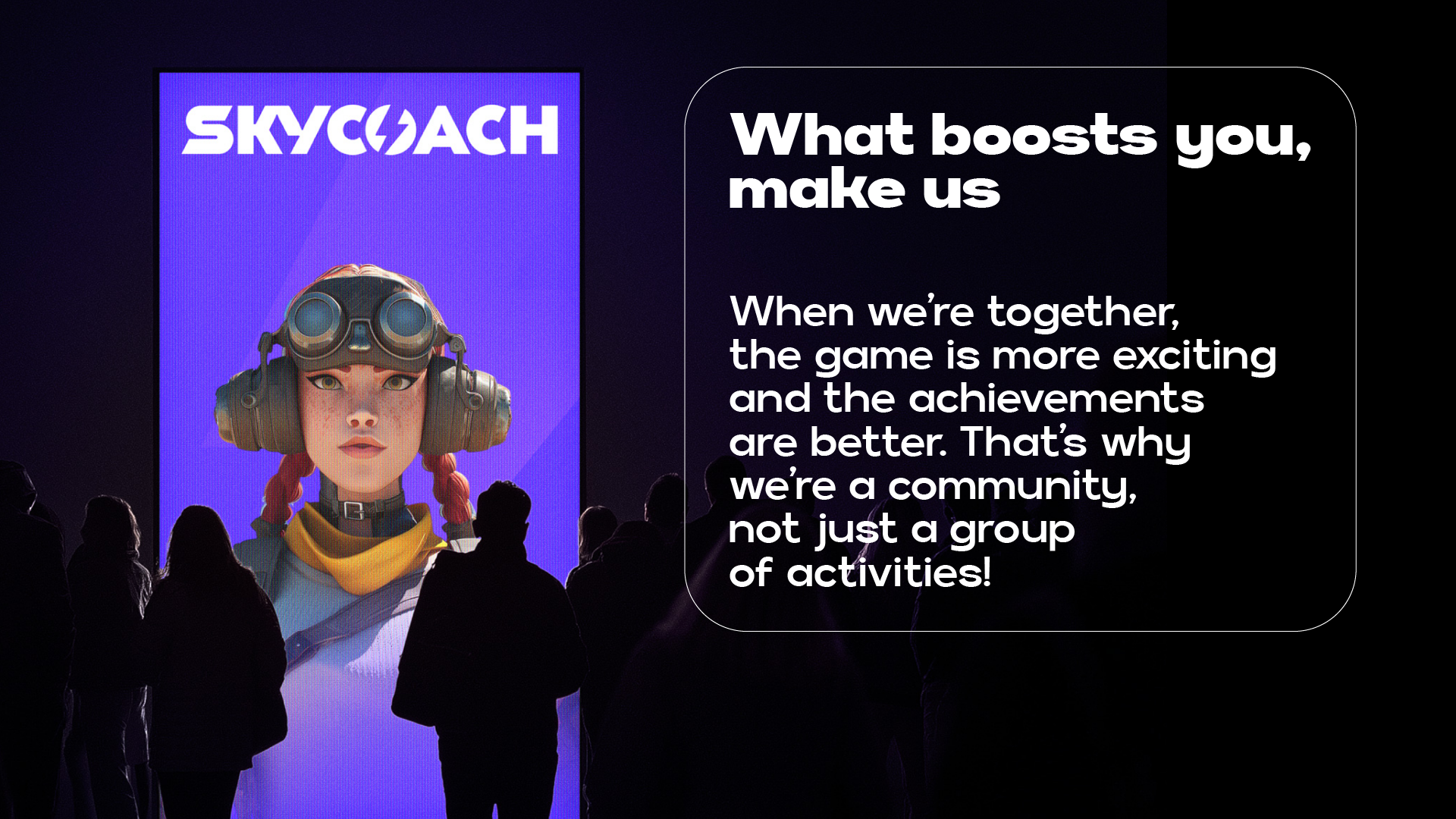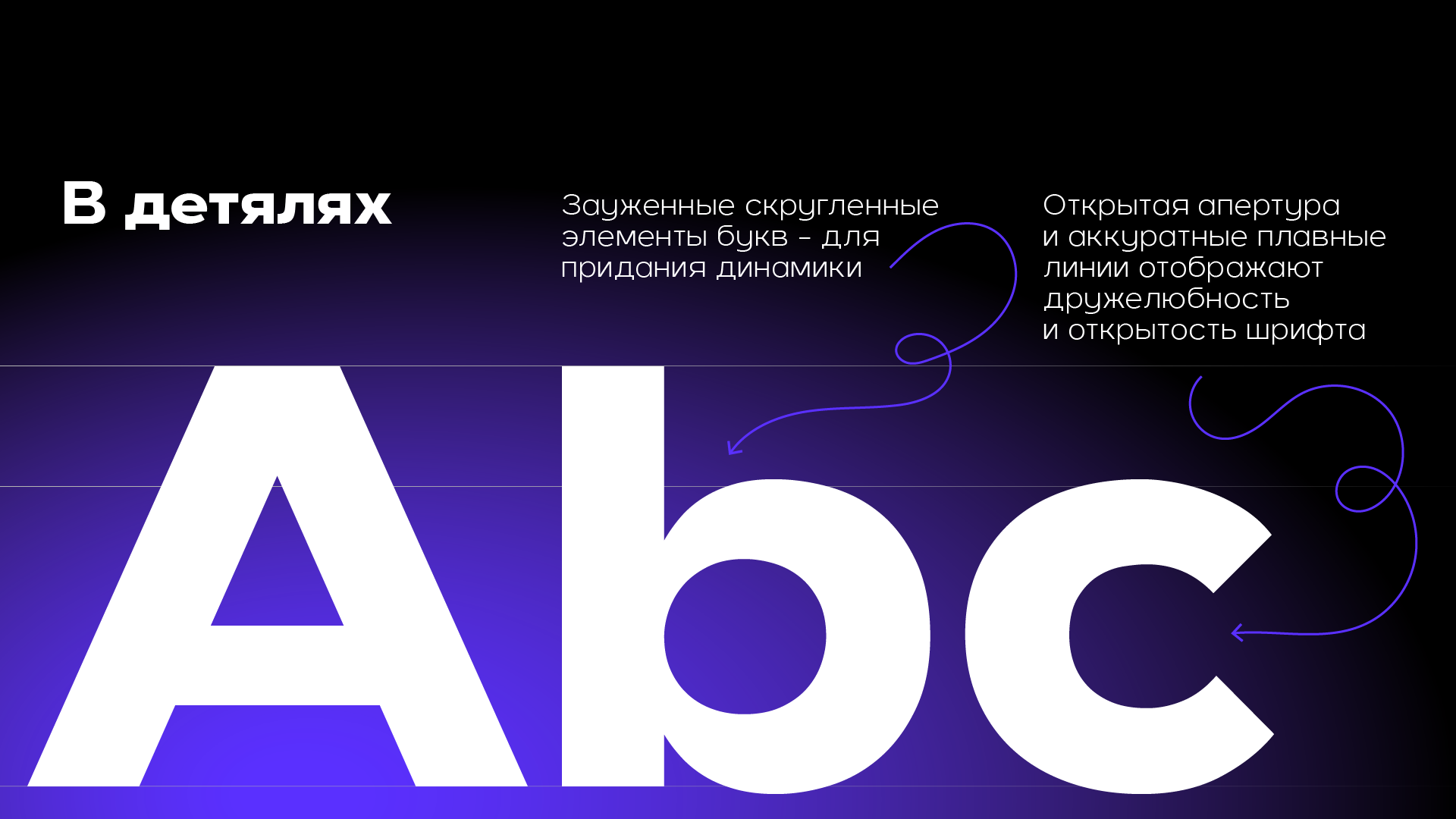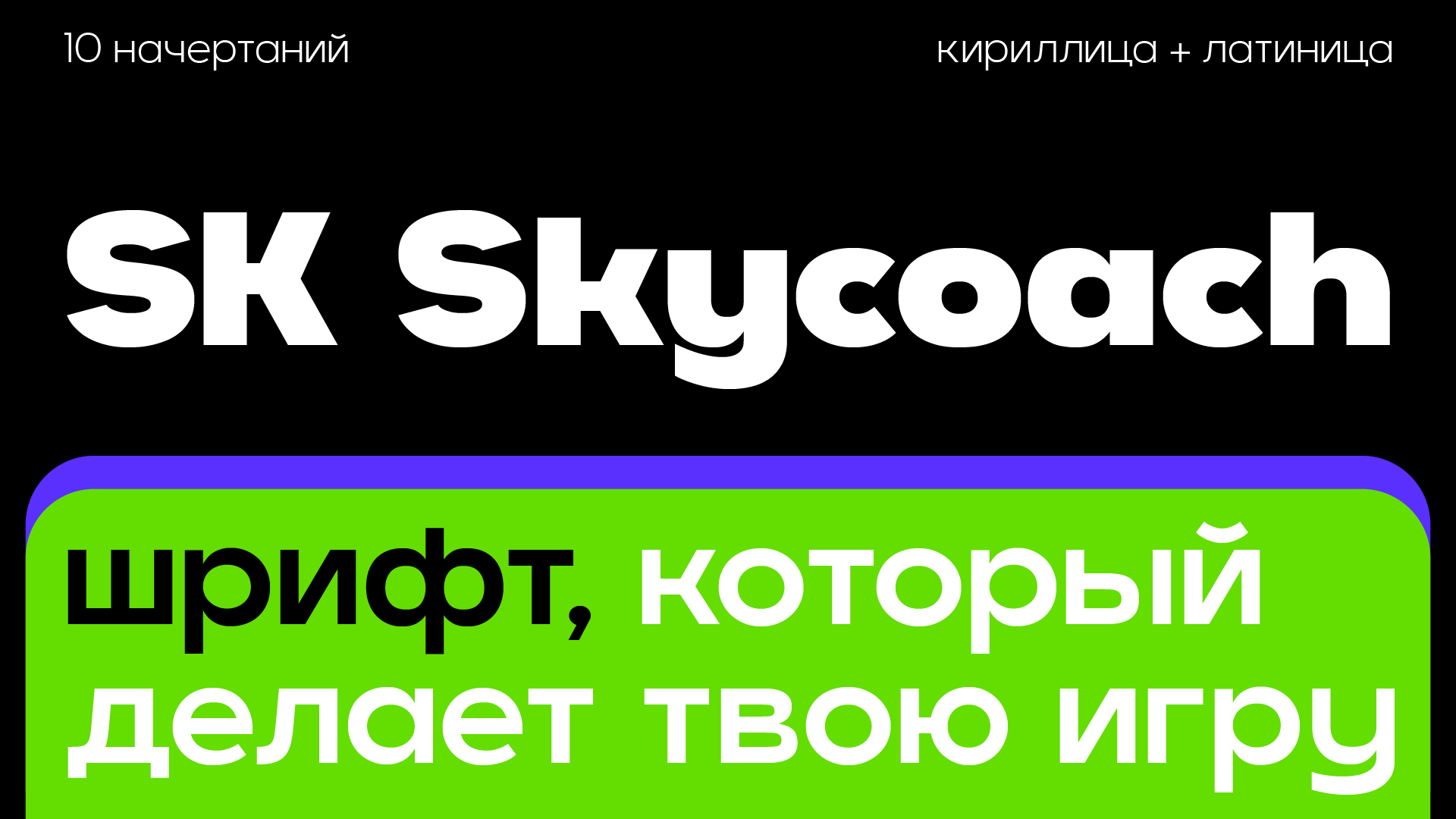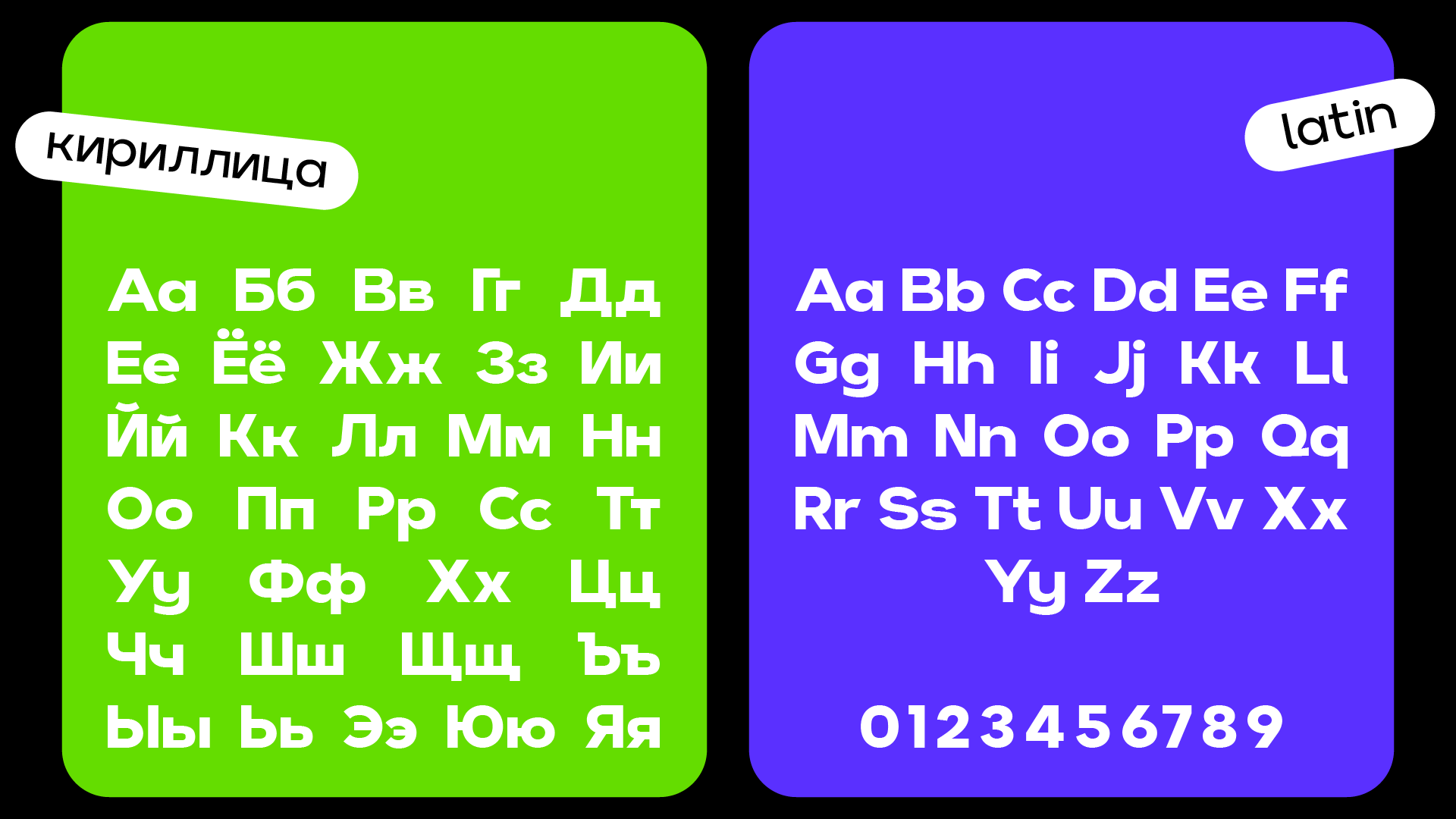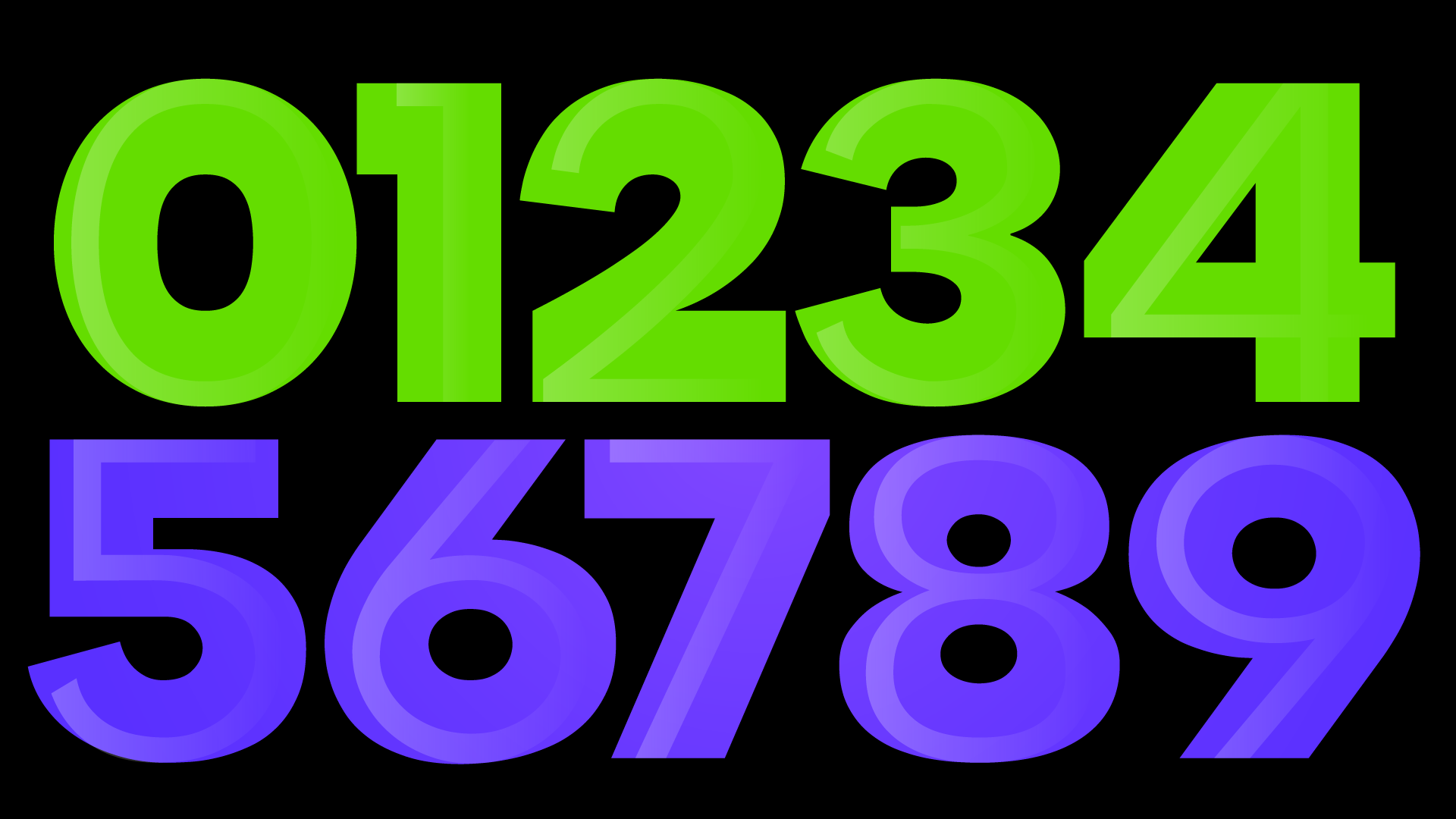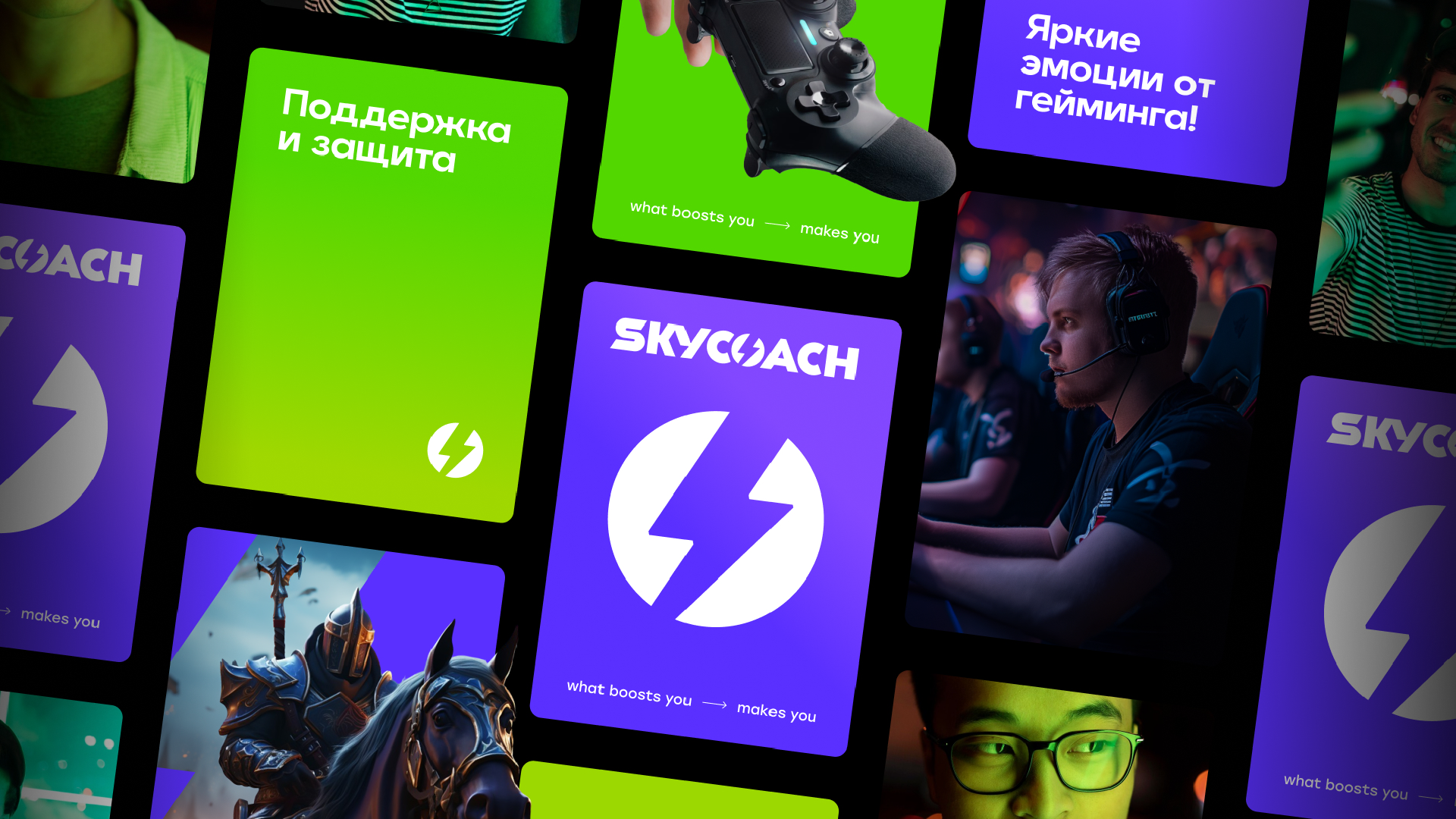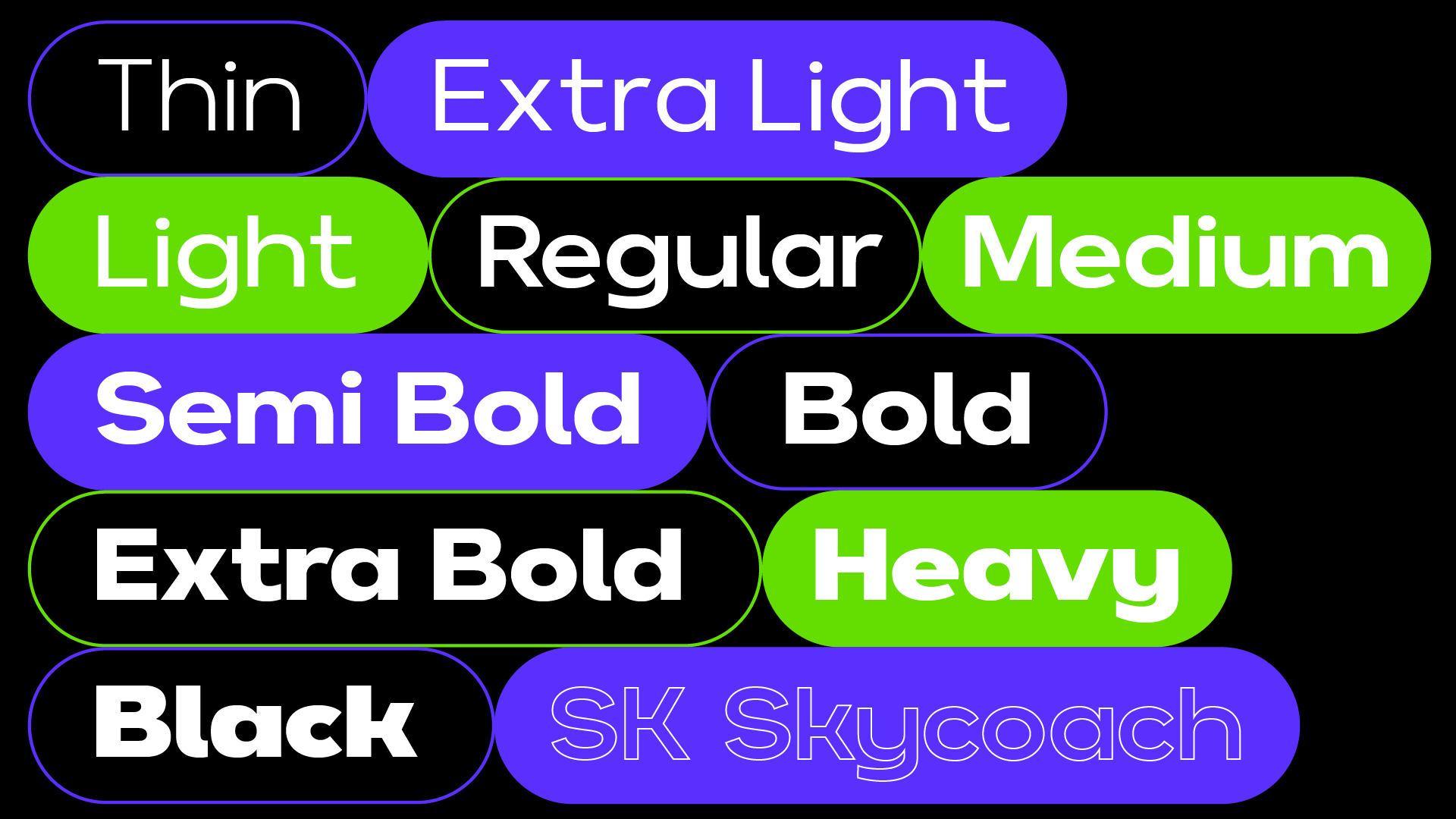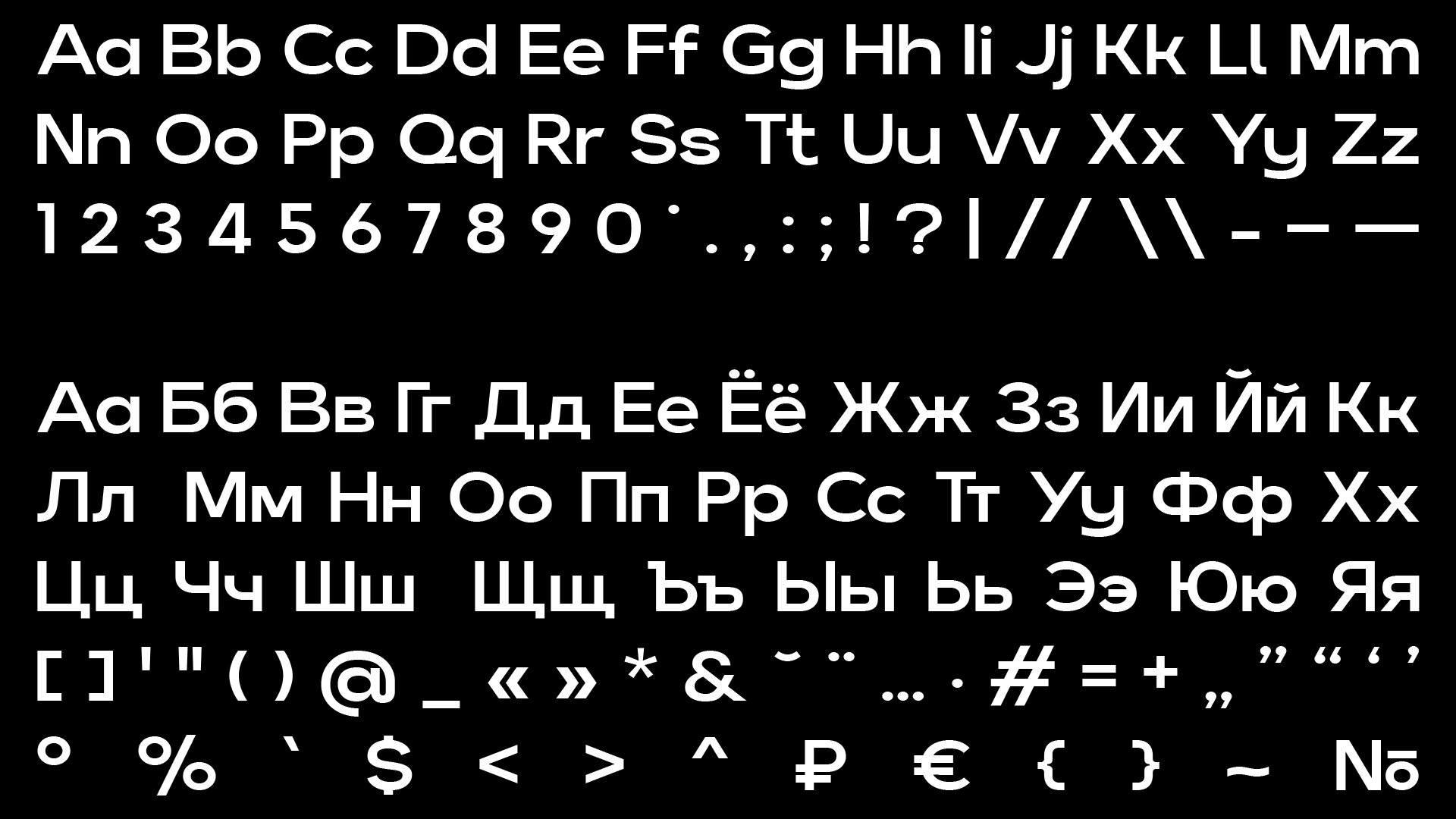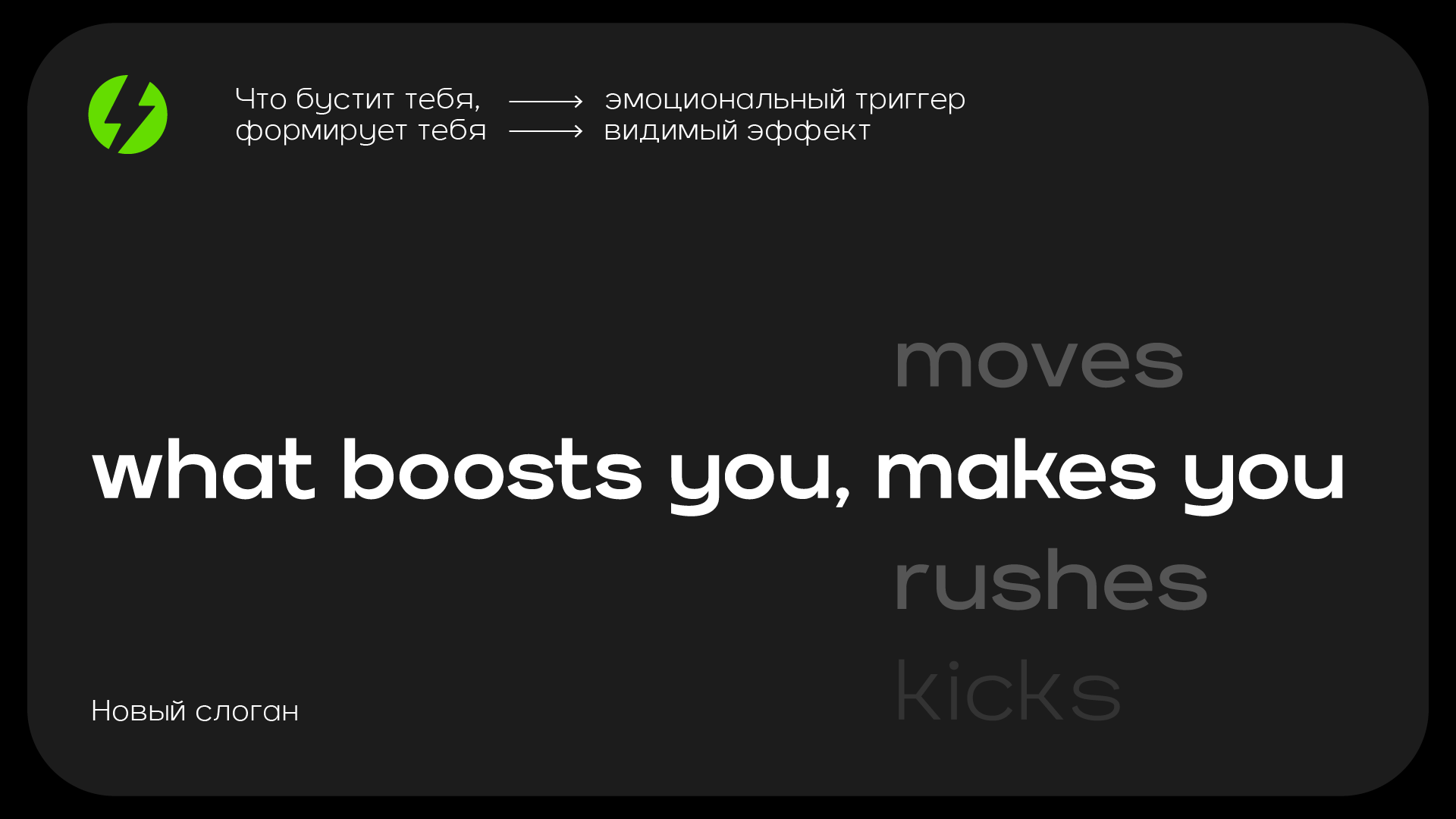
Заказной шрифт
SK Skycoach
Описание работы
Основной целью разработки было создание современного, технологичного шрифта, который мог бы легко применяться на различных платформах и поддерживал как кириллицу, так и латиницу.
Шрифт получил широкий диапазон начертаний — от Thin до Black, что сделало его универсальным инструментом для любых задач: от небольших интерфейсных элементов до громких рекламных заголовков. Тонкие начертания использовались для легких, минималистичных дизайнов, в то время как насыщенные символизировали силу и стабильность, подчеркивая надежность сервиса SkyCoach.
Каждая деталь шрифта была тщательно проработана, чтобы обеспечить высокую читабельность и удобство восприятия на всех устройствах, от мобильных телефонов до мониторов, что идеально сочетается с миссией компании — быть доступной и удобной для всех пользователей.